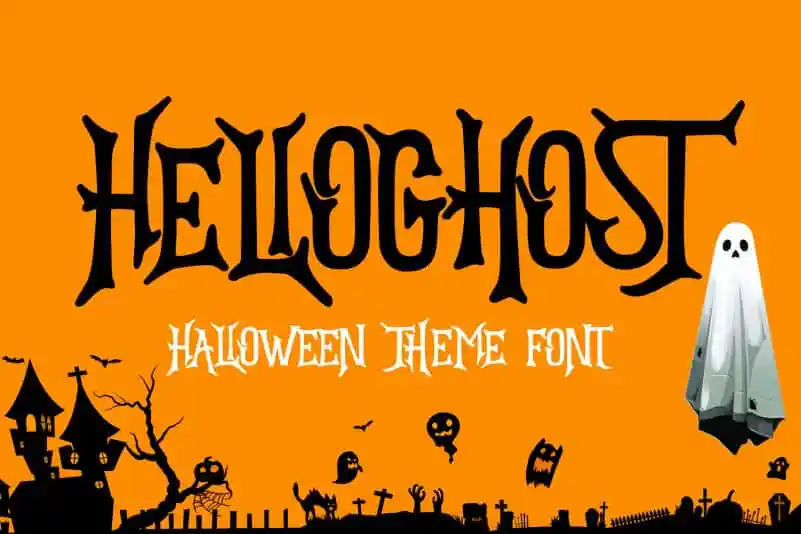
HELLOGHOST – Helloween Theme Font – Download Grátis
A HELLOGHOST – Helloween Theme Font é uma tipografia gothica que se destaca por sua elegância e força inconfundível. Seu design moderno, mas repleto de detalhes históricos, é perfeito para criar ambientes de ficção científica, dark web sites ou qualquer projeto visual que valorize um estilo sobrenatural e tecnológico. Como parte da família Mozarella, a HELLOGHOST mantém o mesmo nível de qualidade e consistência estilística, oferecendo caracteres consistentes e uma fonte completa para uso em diversos tipos de projetos digitais. Esta tipografia é perfeita para designers que buscam dar um toque único ao seu design ou site, seja ele online ou offline.